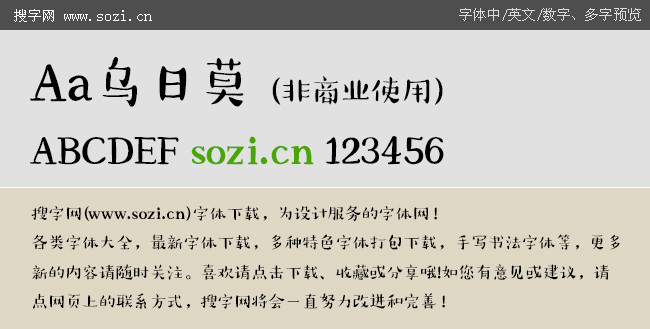
Aa烏日莫(非商業(yè)使用)
搜字網(wǎng)給大家提供一款A(yù)a烏日莫(非商業(yè)使用)中文字體下載,該字體俏皮可愛(ài),充滿(mǎn)童趣,適合包裝畫(huà)冊(cè)等兒童卡通宣傳廣告等應(yīng)用(此字體為個(gè)人非商用版,商用可以聯(lián)系QQ:1006760504)。